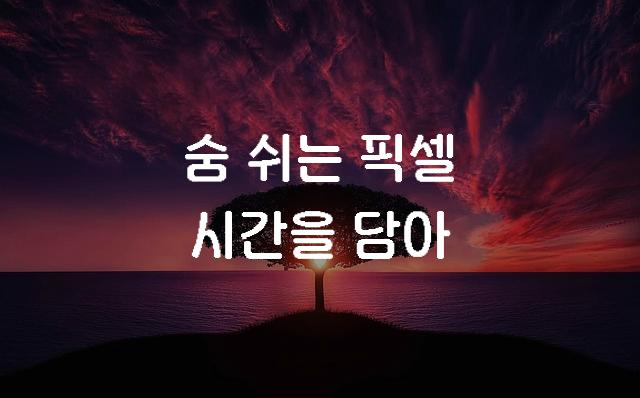
머니그라피-라운디드는 둥근 모서리가 특징인 고딕 스타일의 한국어 폰트로, 따뜻하면서도 친근한 손글씨 느낌을 제공합니다. 사용자에게 부드러운 인상과 함께 읽기 쉬운 경험을 선사합니다.
머니그라피-라운디드은(는)
기본 고딕, 둥근 스타일, 손글씨, 감성적인, 부드러움, 복실복실 계열의 생김새를 가지고 있으며
웹/앱 디자인, 보고서/문서, 출판물 제목 등에서 자주 활용되며, 효과적인 메시지 전달에 적합합니다.
이 폰트는 기술/IT, 금융/비즈니스, 환경/에너지 분야에 잘 어울리며,
명확한, 전문적인, 단순한 느낌을 담고 있는 것이 특징입니다.